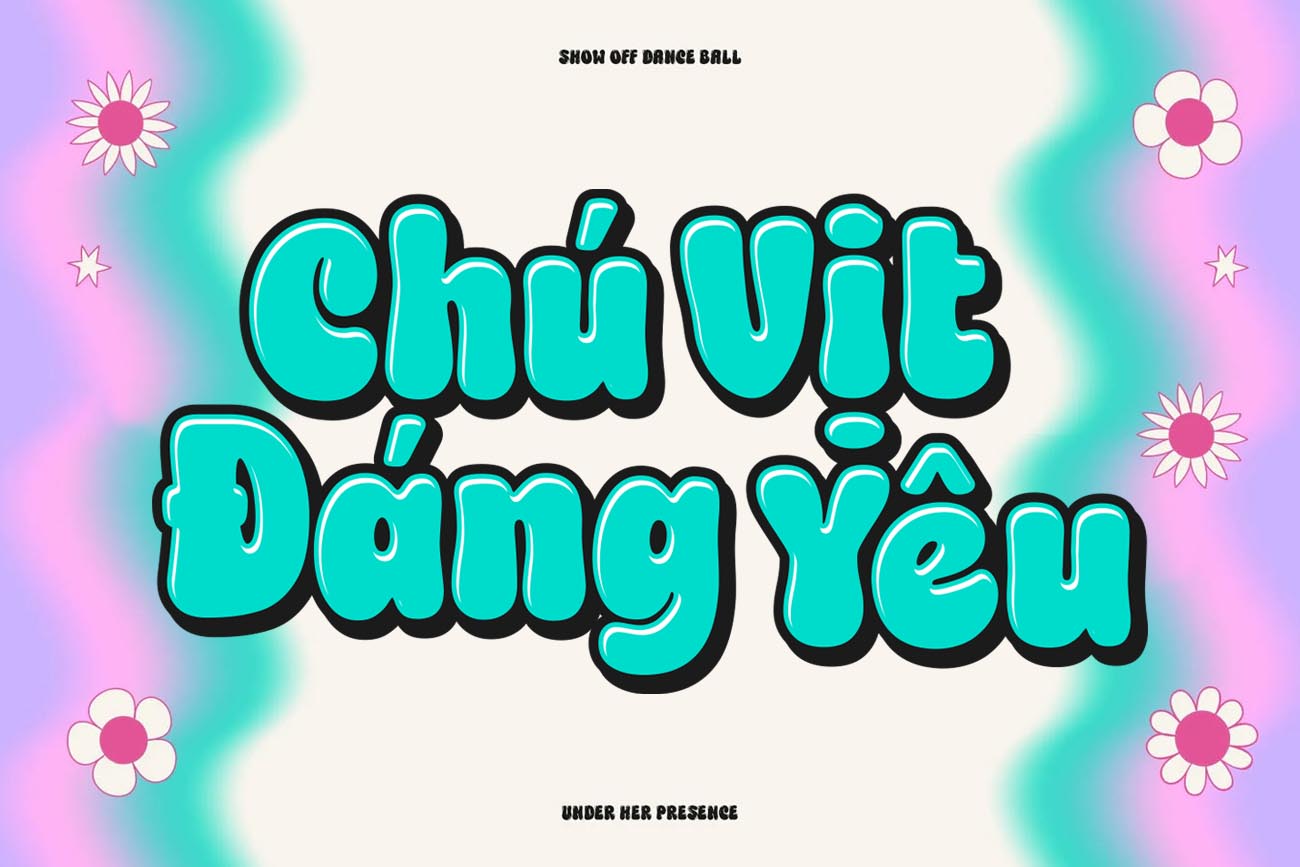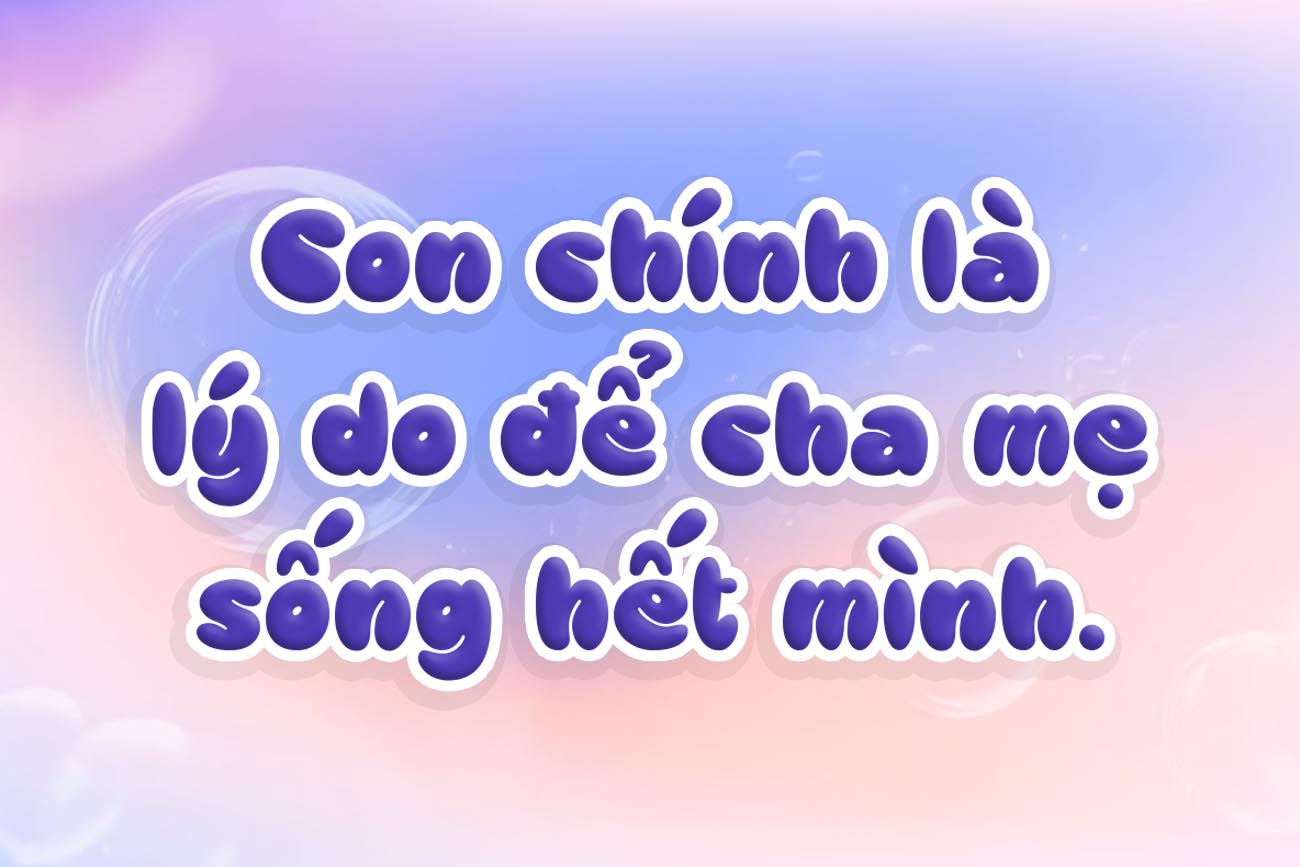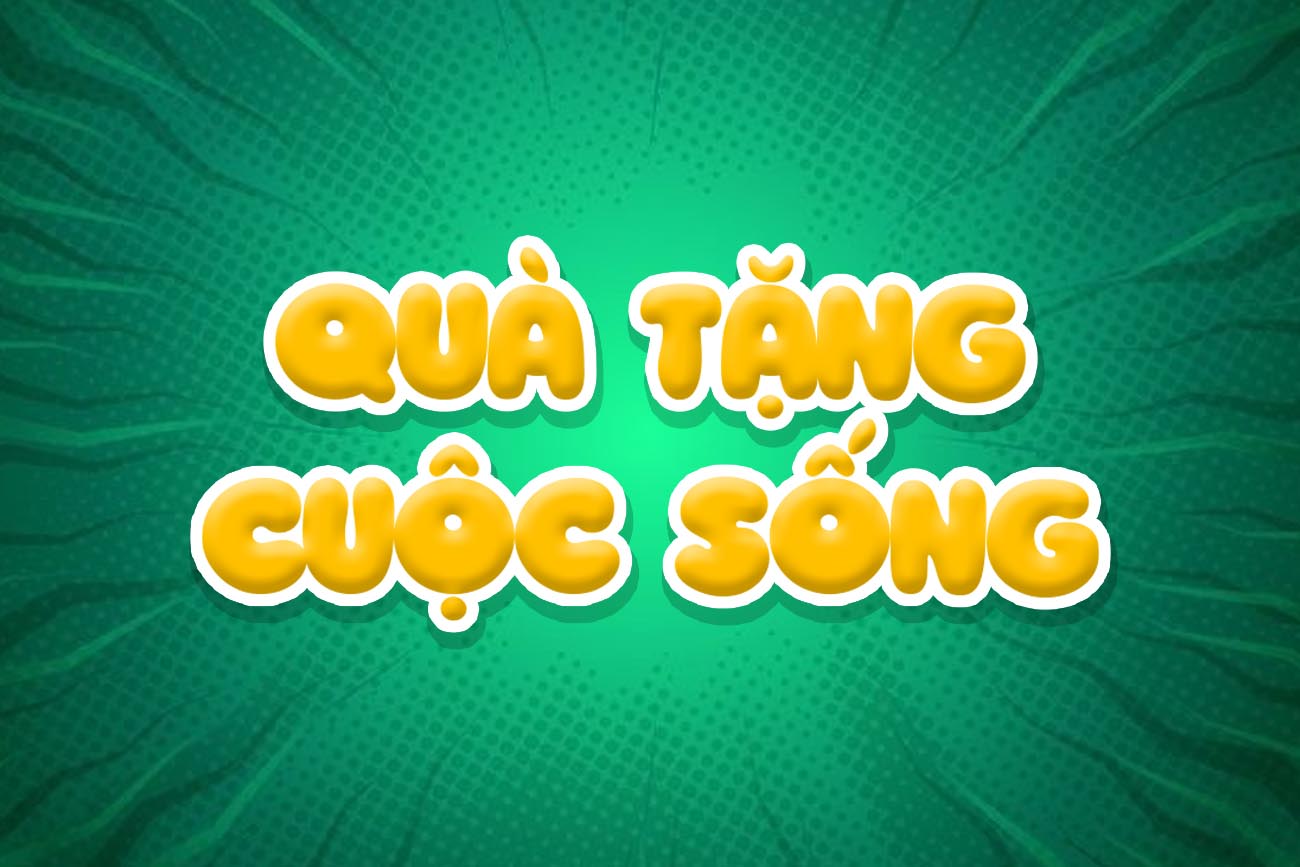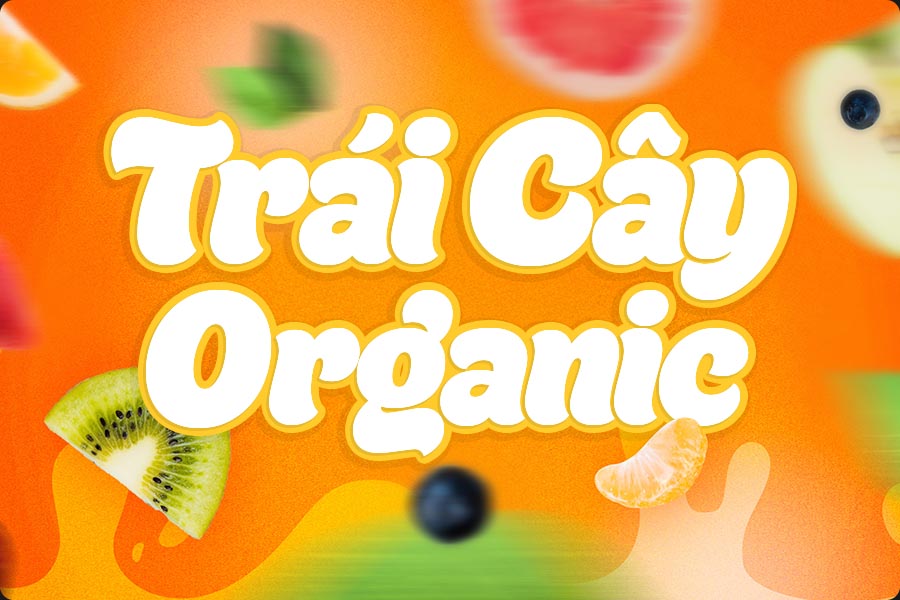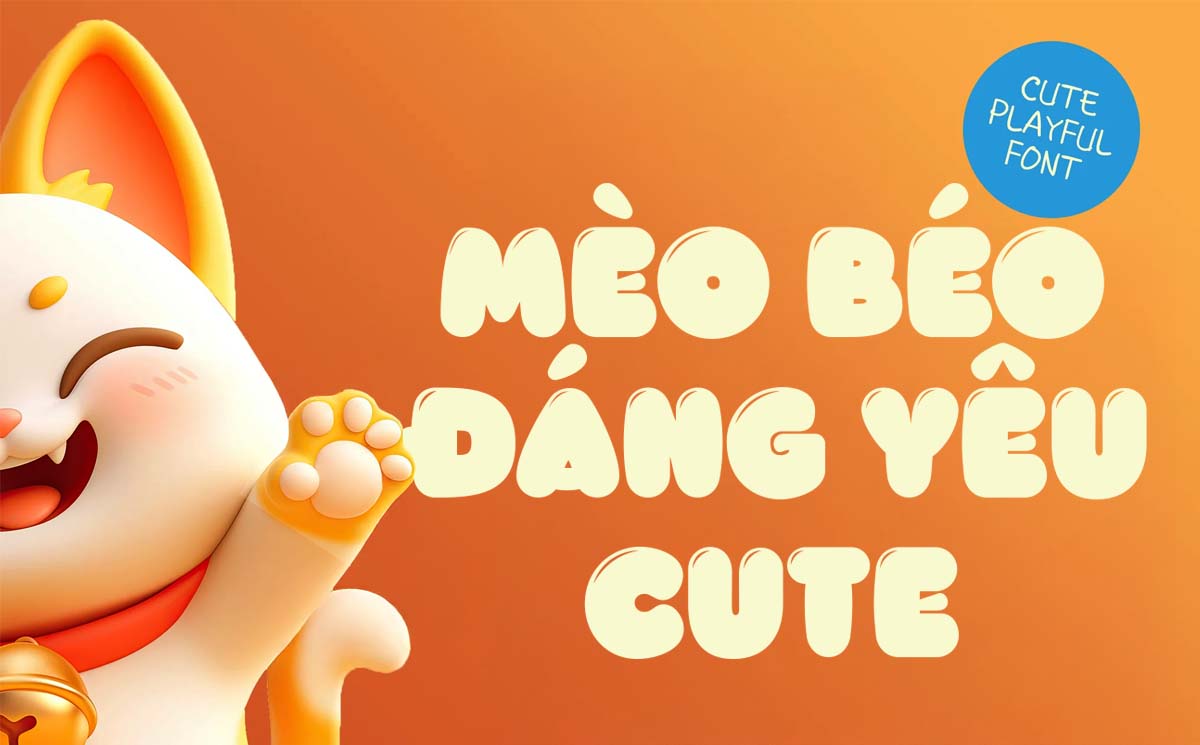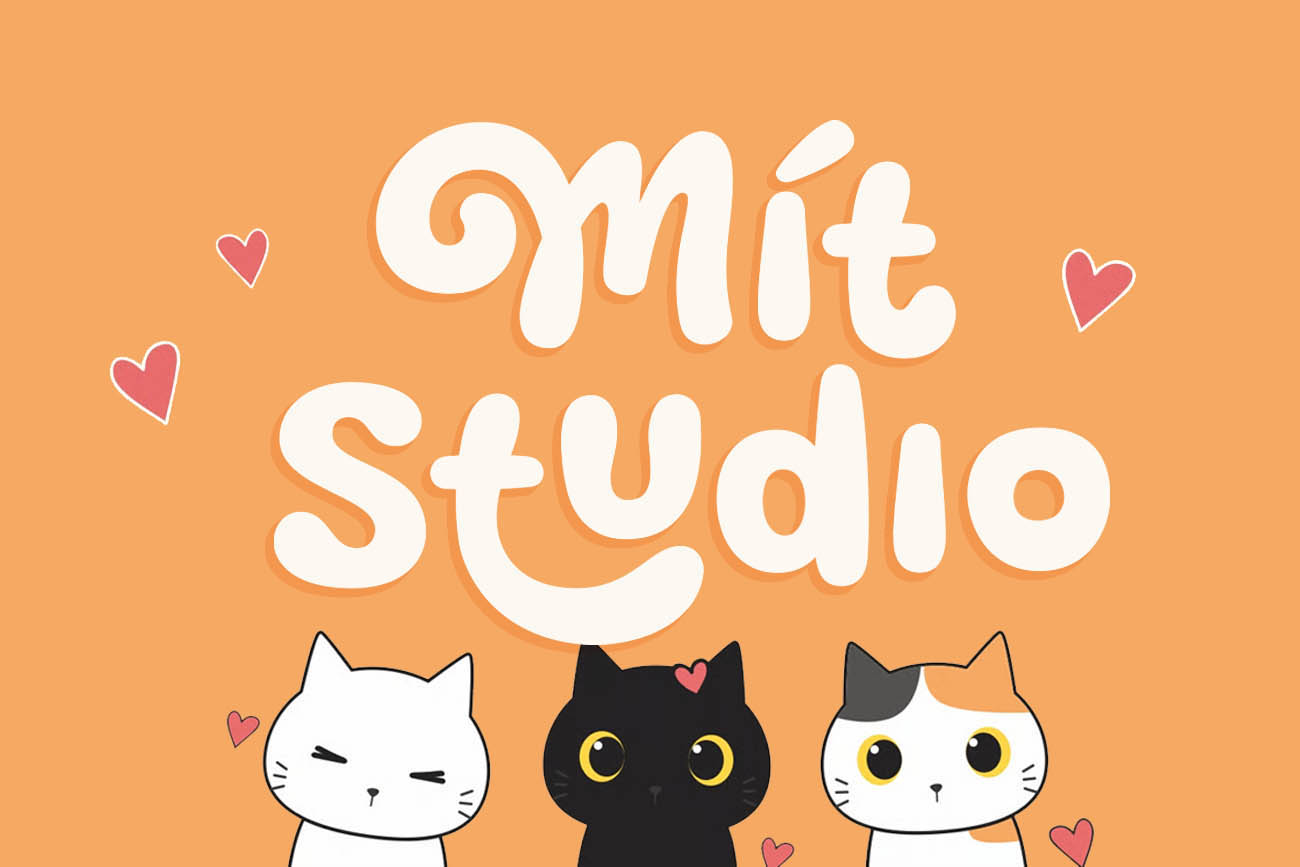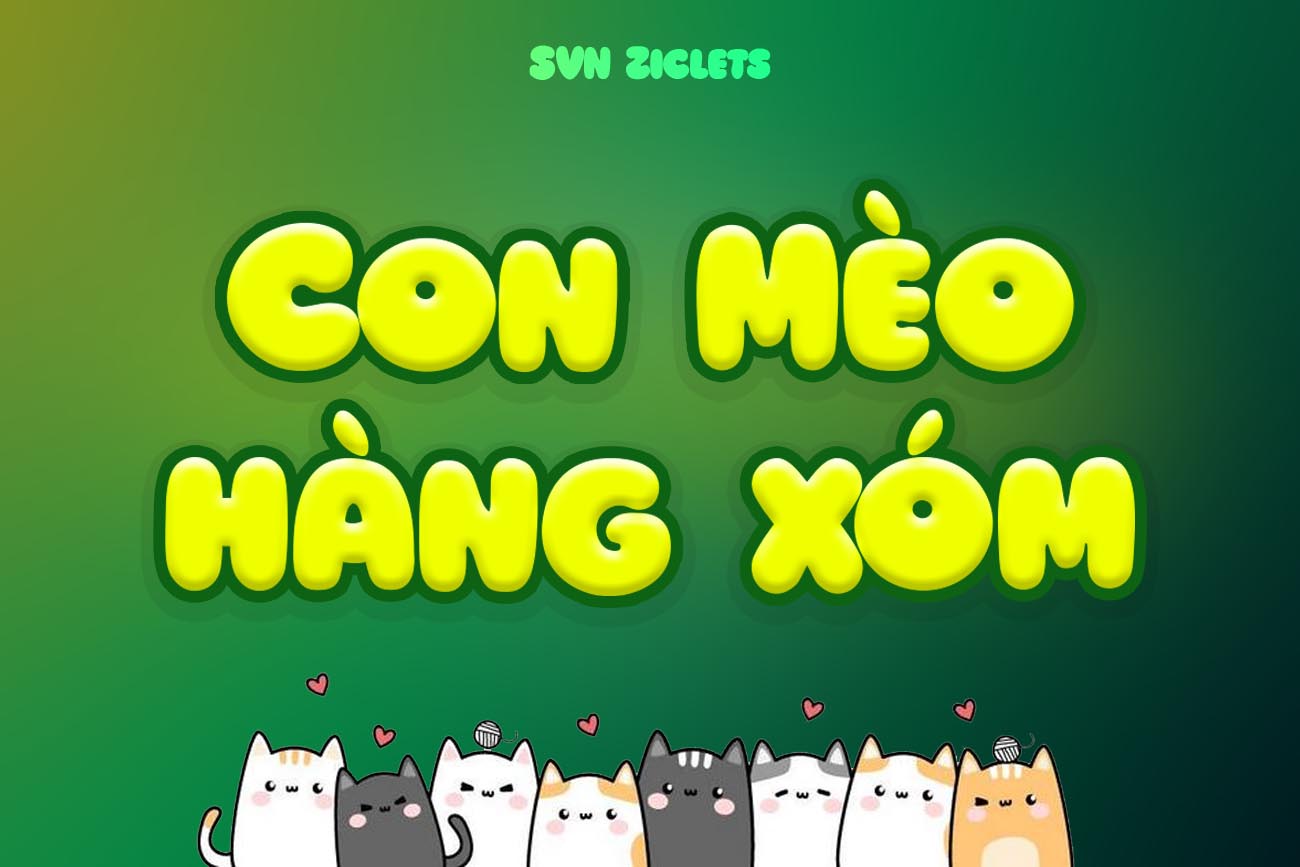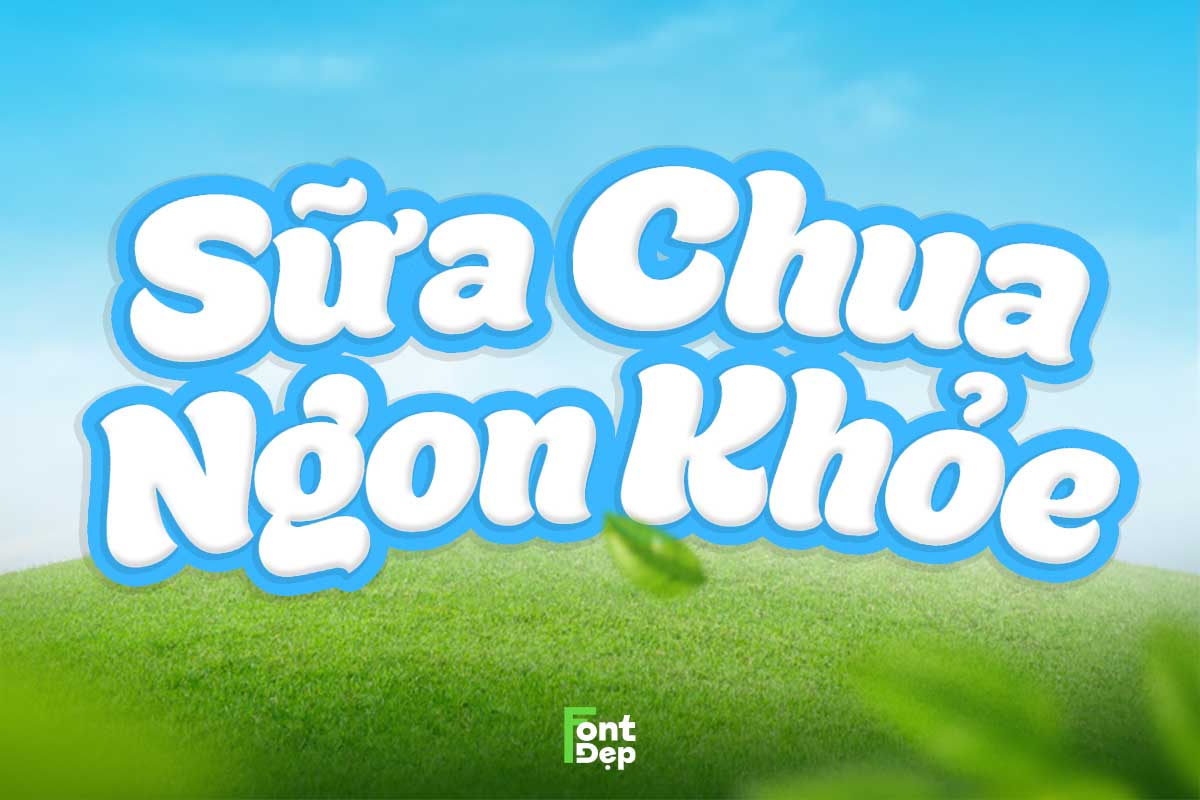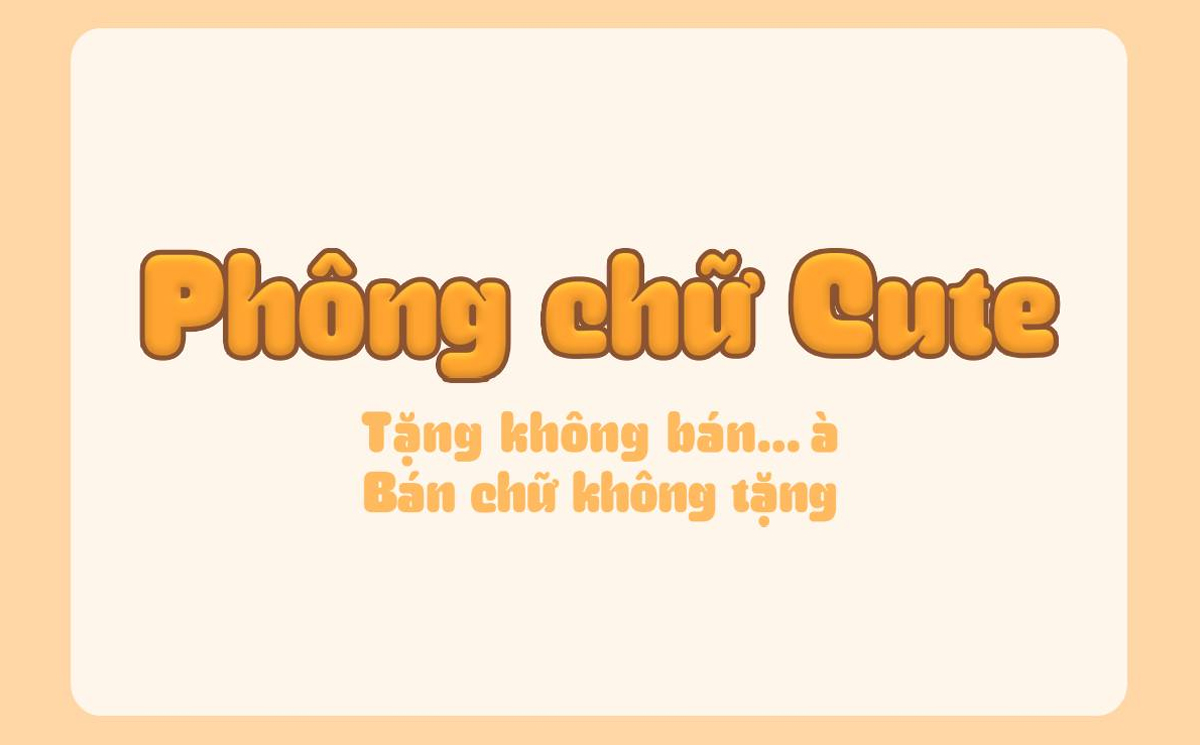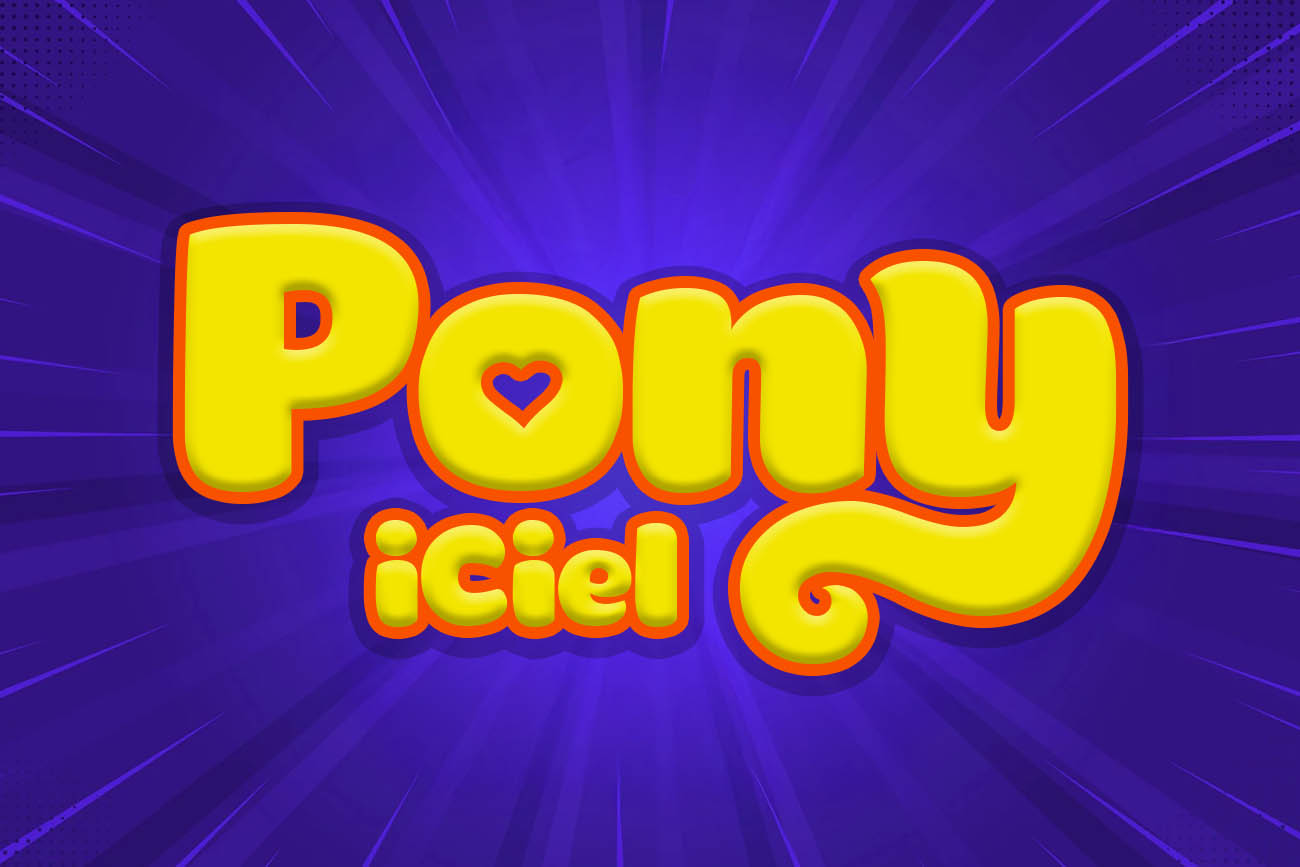
[Tải Xuống] Bộ sưu tập font chữ béo tròn Việt Hóa Đẹp Nhất 2025
Khám phá bộ sưu tập font chữ béo tròn Việt hóa 2025 đáng yêu, dễ đọc, phù hợp thiết kế poster, logo, bao bì và ấn phẩm thiếu nhi tại Fontdep.vn.
Trong thiết kế hiện đại, font chữ không chỉ là công cụ trình bày mà còn là một “ngôn ngữ hình ảnh” để truyền tải cảm xúc. Một trong những phong cách chữ được ưa chuộng nhất hiện nay chính là font chữ béo tròn – hay còn gọi là bubble font. Với các nét chữ dày dặn, bo cong mềm mại, kiểu chữ này mang lại cảm giác gần gũi, đáng yêu và rất bắt mắt.
Tại Fontdep.vn, bạn có thể dễ dàng tìm thấy nhiều bộ font chữ béo tròn Việt hóa đẹp mắt, đáp ứng đầy đủ nhu cầu thiết kế từ poster, logo, bao bì cho đến ấn phẩm học liệu. Nếu bạn muốn làm mới phong cách sáng tạo của mình bằng những kiểu chữ đáng yêu và sinh động, thì bộ sưu tập mà chúng tôi giới thiệu dưới đây chắc chắn sẽ là lựa chọn không thể bỏ qua.
Font chữ béo tròn là gì?
Font chữ béo tròn hay còn gọi là font chữ tròn mập là kiểu chữ có thân chữ dày, phần góc cạnh được bo tròn mượt mà tạo cảm giác mập mạp và vui nhộn. Khác với những font sans-serif thông thường mang nét nghiêm túc, font béo tròn lại thiên về sự thân thiện và gần gũi, rất phù hợp với các thiết kế trẻ trung.
Đặc điểm nổi bật của font chữ béo tròn
- Nét chữ tròn đầy, dễ đọc ở nhiều kích thước.
- Tạo cảm giác vui tươi, hồn nhiên, đặc biệt hợp với đối tượng thiếu nhi.
- Dễ ứng dụng trong in ấn, poster, logo hay bao bì sản phẩm.
- Có khả năng kết hợp màu sắc và hiệu ứng linh hoạt, giúp thiết kế thêm sinh động.
Ứng dụng thực tế của font chữ béo tròn
Font chữ béo tròn không chỉ đáng yêu ở hình dáng mà còn cực kỳ linh hoạt trong nhiều lĩnh vực thiết kế:
- Thương hiệu & logo: Các thương hiệu đồ ăn nhanh, quán cafe hay sản phẩm cho trẻ em thường ưu tiên font béo tròn để tạo cảm giác gần gũi, thân thiện và dễ ghi nhớ.
- Poster lễ hội & sự kiện: Trung thu, Tết Thiếu nhi hay Noel… đều cần không khí tươi vui và sinh động, và font chữ béo tròn chính là lựa chọn giúp thiết kế trở nên nổi bật.
- Bao bì & menu sản phẩm: Từ snack, đồ uống đến hộp quà, việc dùng font béo tròn giúp sản phẩm thêm phần bắt mắt và hấp dẫn hơn.
- Học liệu & ấn phẩm thiếu nhi: Với ưu điểm dễ đọc, dễ ghi nhớ, font chữ béo tròn rất phù hợp cho flashcard, sách tập đọc hay poster trong lớp học.
Bộ sưu tập font chữ béo tròn Việt hóa đẹp nhất 2025
1. Font chữ iCiel Pony Việt hóa – Ngộ nghĩnh & Sinh động
Font iCiel Pony được thiết kế với các ký tự tròn mập, bo cong đều đặn và mang chút phá cách ở chi tiết trang trí, tạo nên cảm giác vui nhộn và dễ thương. Đường nét chắc khỏe nhưng vẫn giữ được sự mềm mại, khiến chữ nổi bật và dễ đọc. Với phong cách sinh động và gần gũi, font này rất phù hợp cho poster thiếu nhi, tiêu đề sáng tạo và các thiết kế bao bì sản phẩm vui nhộn.
2. Font chữ iCiel Cadena miễn phí – Béo tròn & Đáng yêu
Font iCiel Cadena gây ấn tượng với những đường nét dày dặn, bo tròn mềm mại, tạo cảm giác mập mạp và đầy sức sống. Kiểu dáng tròn đều giúp chữ trở nên nổi bật, dễ đọc và mang lại sự gần gũi, thân thiện. Nhờ phong cách vui nhộn và tự nhiên, font này rất phù hợp để sử dụng trong poster thiếu nhi, tiêu đề bắt mắt hay các thiết kế quảng bá sản phẩm sáng tạo.
3. Phông chữ TH Playful Bubble – Vui nhộn & Ngộ nghĩnh
Font TH Playful Bubble mang dáng chữ tròn phồng đặc trưng, các đường nét mập mạp và liền mạch gợi cảm giác sôi động và đáng yêu. Từng ký tự được thiết kế như những bong bóng nhỏ, tạo sự gần gũi và dễ gây ấn tượng với người xem. Kiểu chữ này rất thích hợp cho thiết kế tiêu đề, poster sự kiện hay các sản phẩm hướng đến thiếu nhi và giới trẻ.
- Tác giả gốc: Flat
- Việt hóa bởi: Phạm Sơn - Admin S99, Fontdep.vn
4. SVN Ziclets – Ngộ nghĩnh & Tròn trịa
Font SVN Ziclets nổi bật với những ký tự phồng to, tròn đều và liền mạch, mang lại cảm giác vui nhộn và gần gũi. Các đường nét tròn mập giúp chữ trở nên sinh động, dễ gây ấn tượng ngay từ cái nhìn đầu tiên. Với phong cách dí dỏm và trẻ trung, font này phù hợp cho tiêu đề poster, thiết kế bao bì cũng như các ấn phẩm hướng đến thiếu nhi.
- Tác giả gốc: Hanoded
- Việt hóa bởi: STYLEno.1 Fonts
5. TH Tijuf Regular – Dễ thương & Tròn đầy
Font TH Tijuf Regular mang nét chữ phồng tròn mềm mại, các ký tự có độ dày đồng đều và tạo cảm giác đáng yêu, vui nhộn. Kiểu dáng tròn mập giúp chữ trở nên nổi bật, dễ gây thiện cảm ngay từ cái nhìn đầu tiên. Với sự ngộ nghĩnh và thân thiện trong từng đường nét, font này đặc biệt phù hợp để thiết kế poster, tiêu đề hoặc các ấn phẩm dành cho thiếu nhi.
Có thể thấy, font chữ béo tròn không chỉ là lựa chọn mang tính nhất thời mà đang dần trở thành xu hướng thiết kế lâu dài, đặc biệt trong các sản phẩm sáng tạo tại Việt Nam. Nhờ sự thân thiện, dễ thương và tính ứng dụng đa dạng, dòng font này luôn mang đến cho nhà thiết kế nhiều ý tưởng độc đáo và mới mẻ.